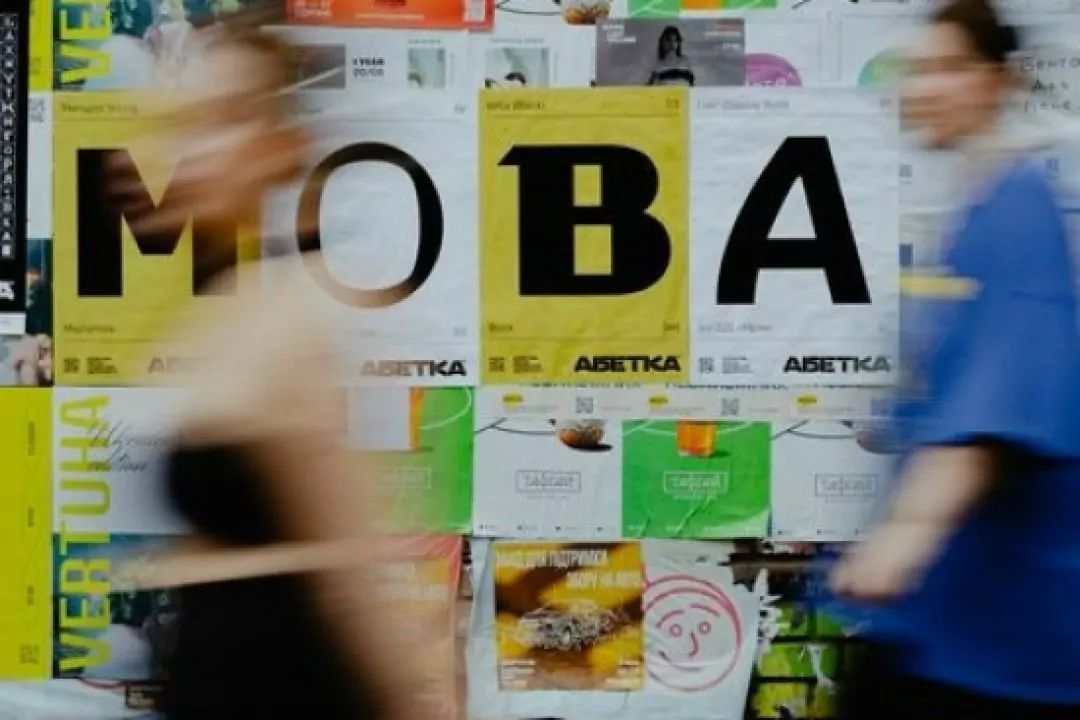
Український шрифт “Абетка” здобув перемогу на конкурсі European Design Awards
Шрифт “Шрифтова абетка української ідентичності” переміг на щорічному європейських конкурсів у галузі комунікаційного дизайну European Design Awards.
Український шрифт здобув золото в категорії Integrated Identity Application, а також головну нагороду Jury Prize.
Як повідомив голова Projector Creative & Tech Online Institute Олександр Трегубов, журі обрали український шрифт переможцем одноголосно.
"Шрифтова абетка української ідентичності" — це історія української боротьби від "А" до "Я", зазначають на сайті проєкту.
“Кожна літера нашої абетки присвячена одному символу, без якого Україна не була б тією державою, яку ми знаємо, любимо та за яку стоїмо. На сторінках цього проєкту ви знайдете 33 події, постаті, символи та знаки, що супроводжували Україну на шляху до відновлення незалежності в 1991 році та підтримують нас у боротьбі за неї зараз”, — пояснюють автори проєкту.
Літеру "А" в абетці присвятили АН-"Мрія", "Б" — будинку "Слово", "В" — волі, "Г" — Голодомору. Також серед важливих українських символів, подій та постатей є живий ланцюг, чорнобильська катастрофа, шлях із варяг у греки, Хрещення Русі, протитанковий їжак, Іван Франко, тризуб Володимира Великого, “Енеїда” та багато інших.
"Шрифтову абетку української ідентичності" розробили онлайн-інститут Projector і медіа Telegraph Design за підтримки Фундації "ЗМІН".